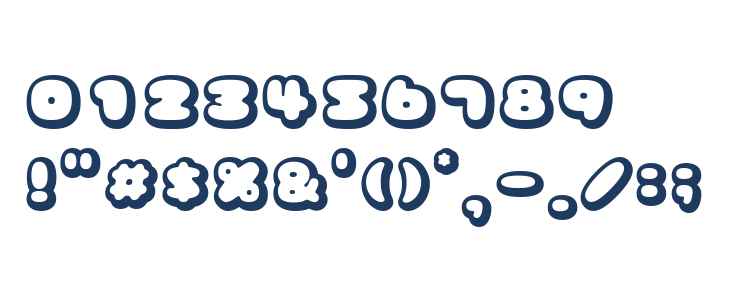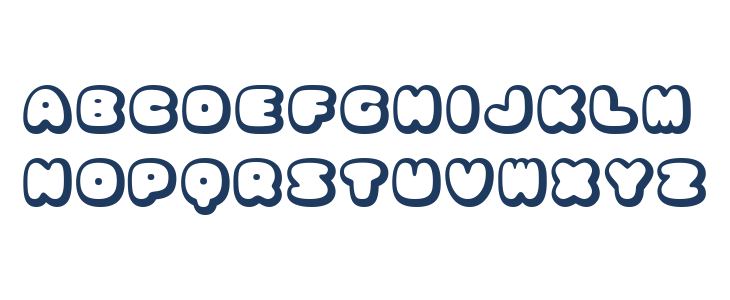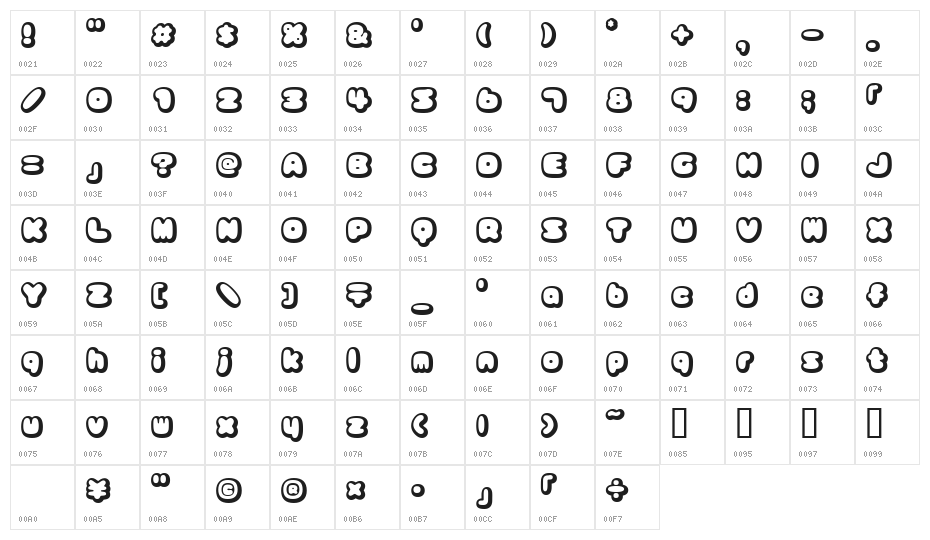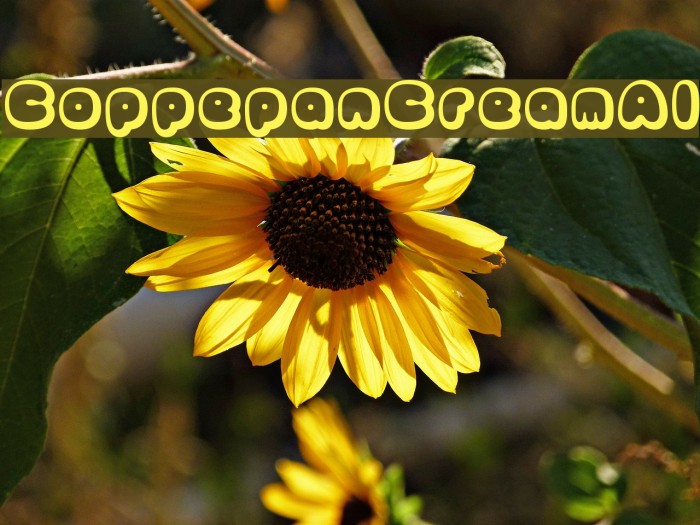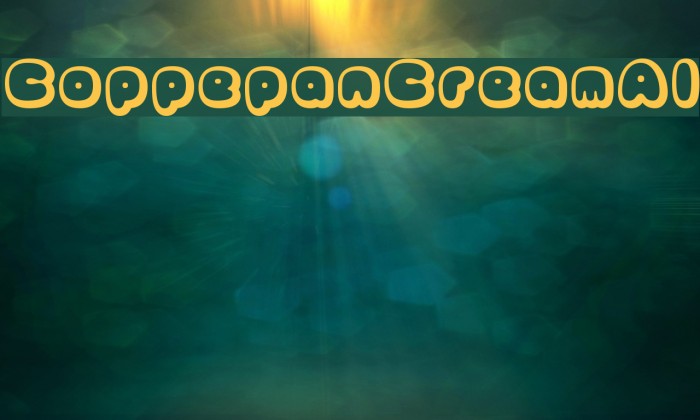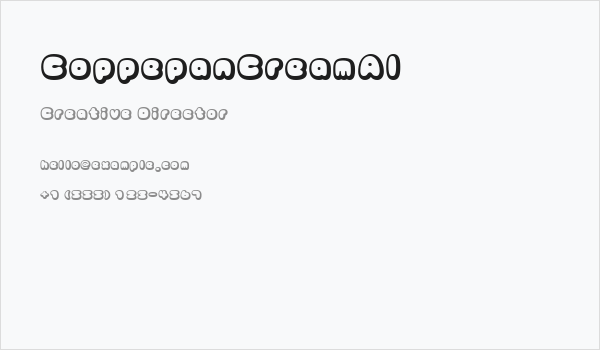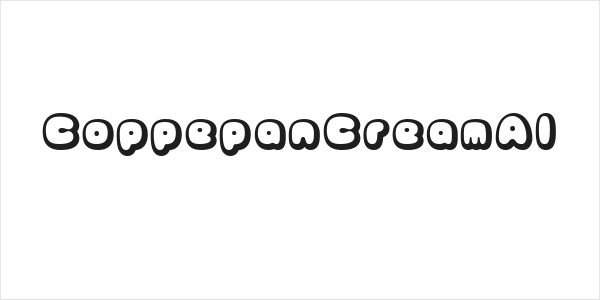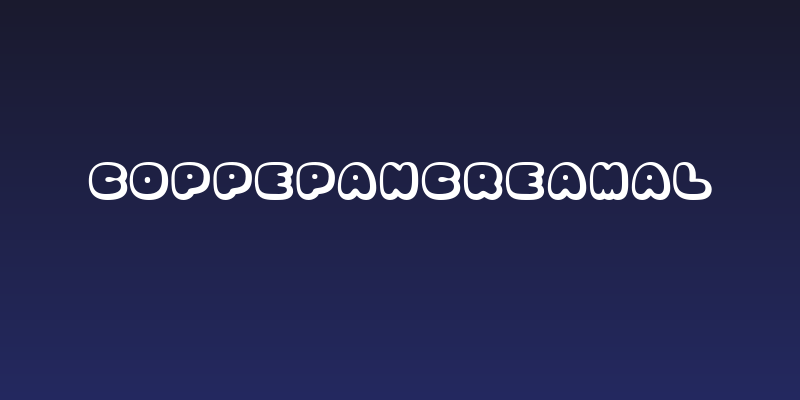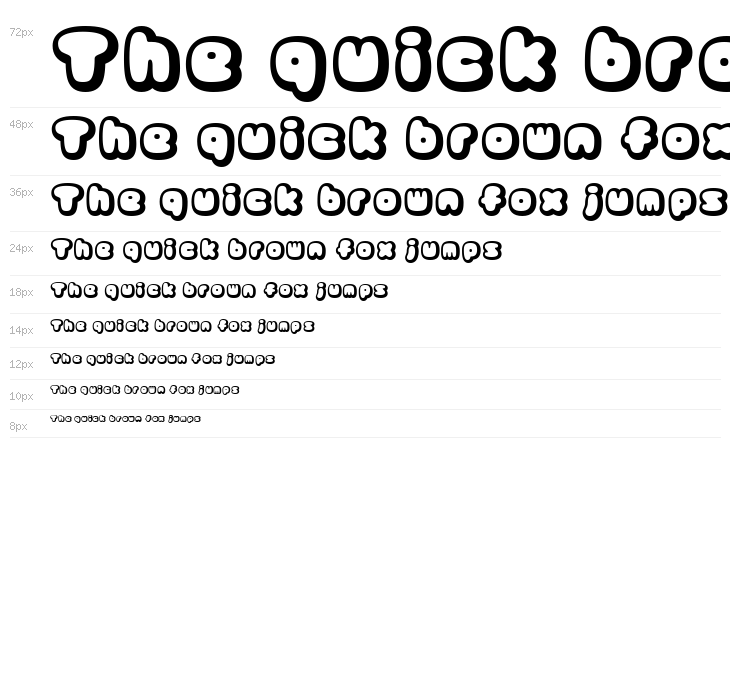
CoppepanCreamAl Font
| Stile generale | Playful, Cartoonish, Fun |
| Progetti proposti | Ideal for children's books, playful branding, party invitations, and cartoon-themed designs. |